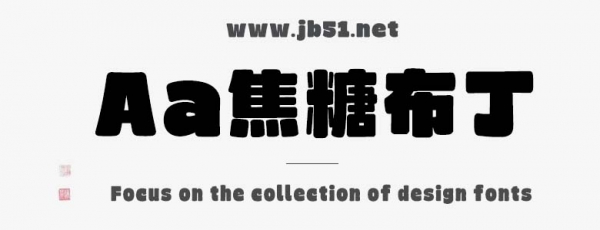
Aa焦糖布丁由Aa字庫(kù)出品的藝術(shù)字體,字體筆觸粗實(shí),字形端正,適合應(yīng)用于藝術(shù)設(shè)計(jì)、平面宣傳設(shè)計(jì)、網(wǎng)頁(yè)設(shè)計(jì),書(shū)法字帖等領(lǐng)域。有需要的朋友快來(lái)本站下載使用吧。